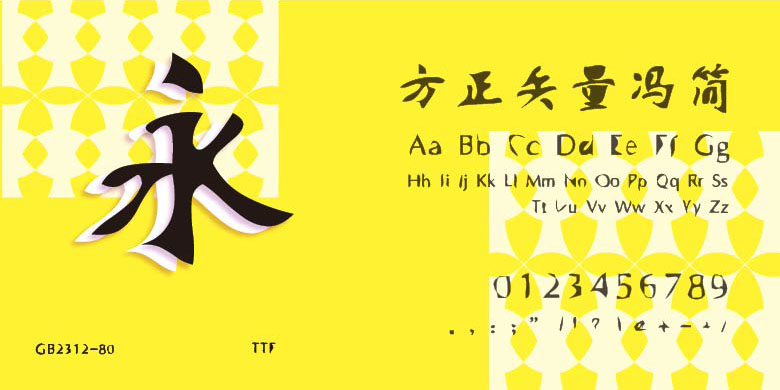
方正矢量冯
方正矢量冯,这款字体结构工整、笔画清晰,兼顾美观与易读性,适用于标题、正文、海报、包装、LOGO 等多种场景。字形优雅稳定,风格百搭耐看,适配日常排版与创意设计,让文字呈现更舒适、更具质感。方正矢量冯一笔一画,皆是细节,以均衡的比例、流畅的线条打造舒适视觉体验,字形端正大气,风格简约现代。无论是商业设计、品牌宣传还是日常排版,都能轻松驾驭,让文字更有格调与力量。方正矢量冯字体下载。
字体品牌: 方正字库 设计师:冯梦波 字体分类:创意字体 字体属性:精品字 字符集:大陆简体(GB2312-80) 发布时间: 2011
方正矢量冯的灵感来自设计者幼年摹写古代碑帖的经验。这款字体通过调整电脑参数来模拟碑帖拓本中文字的“风化”效果,从而在可读和不可读之间达到平衡。电脑参数将字形和笔画进行了减并压缩,形成黑白图案,飘逸峭拔,颇具瘦峻的金石之风。方正矢量冯带有艺术实验性,有一定的识别度,可用于广告和产品包装的设计。